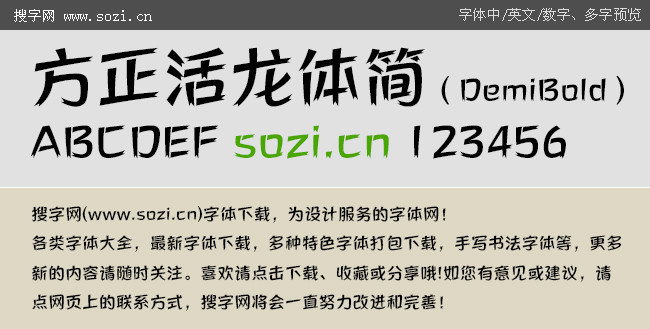
方正活龍?bào)w簡DemiBold
搜字網(wǎng)提供一款方正活龍?bào)w簡中文字體下載,方正活龍?bào)w簡是方正字庫全新開發(fā)的一款非常實(shí)用的字體,該字體特點(diǎn)是橫、直劃粗細(xì)平均,所有筆劃頭部斜直而末端開了叉口,而且點(diǎn),撇,捺,抅等都是弧形,沒有垂直平行線的,橫劃重心向右上方斜上,讓它活一些,有動感和速度,像一條龍?jiān)谔炜诊w舞,可以應(yīng)用于網(wǎng)頁設(shè)計(jì)、包裝設(shè)計(jì)、海報(bào)設(shè)計(jì)等廣告設(shè)計(jì)場合使用。